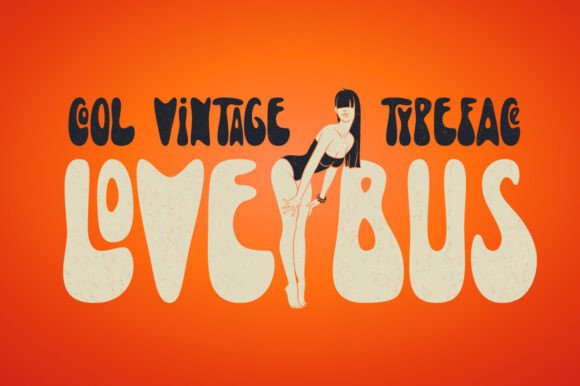
Lovebus
Lovebus: A Fonte Vintage que Revive o Espírito dos Anos 60
Se você está em busca de uma tipografia que traga o charme psicodélico dos anos 60 para seus projetos, a Lovebus é a escolha perfeita. Inspirada na era hippie, essa fonte vintage combina estilo retro com funcionalidades modernas, garantindo autenticidade e originalidade em cada detalhe.
- Design inspirado nos anos 60 – linhas fluidas e curvas que remetem à cultura psicodélica e à liberdade da época.
- 26 ligaturas automáticas – substituições inteligentes que dão ao seu texto um visual único sem esforço adicional.
- Versatilidade criativa – ideal para capas de álbuns, posters, convites, branding, sites e tudo que precisar de um toque retro.
- Alta legibilidade – apesar do estilo ousado, a Lovebus mantém clareza em tamanhos pequenos e grandes.
Por que a Lovebus se destaca no mercado?
Ao contrário de fontes genéricas, a Lovebus foi cuidadosamente desenvolvida para quem deseja reviver a estética vintage sem sacrificar a modernidade. As ligaturas embutidas permitem que você crie composições tipográficas exclusivas com apenas alguns cliques, economizando tempo e elevando o nível de profissionalismo.
Onde usar a Lovebus?
- Cartazes de festivais de música e eventos culturais.
- Identidade visual de marcas que buscam um apelo nostálgico.
- Convites de casamentos temáticos, festas retrô ou aniversários psicodélicos.
- Design de capas de livros, álbuns e revistas.
- Elementos de UI/UX que precisam de um toque vintage em sites e apps.
A fonte Lovebus oferece muito mais que um visual retro; ela entrega funcionalidade avançada com suas ligaturas automáticas, garantindo que seu projeto se destaque de forma autêntica e criativa. Seja para designers experientes ou iniciantes, a Lovebus é um investimento que traz o espírito hippie dos anos 60 direto para o seu teclado.